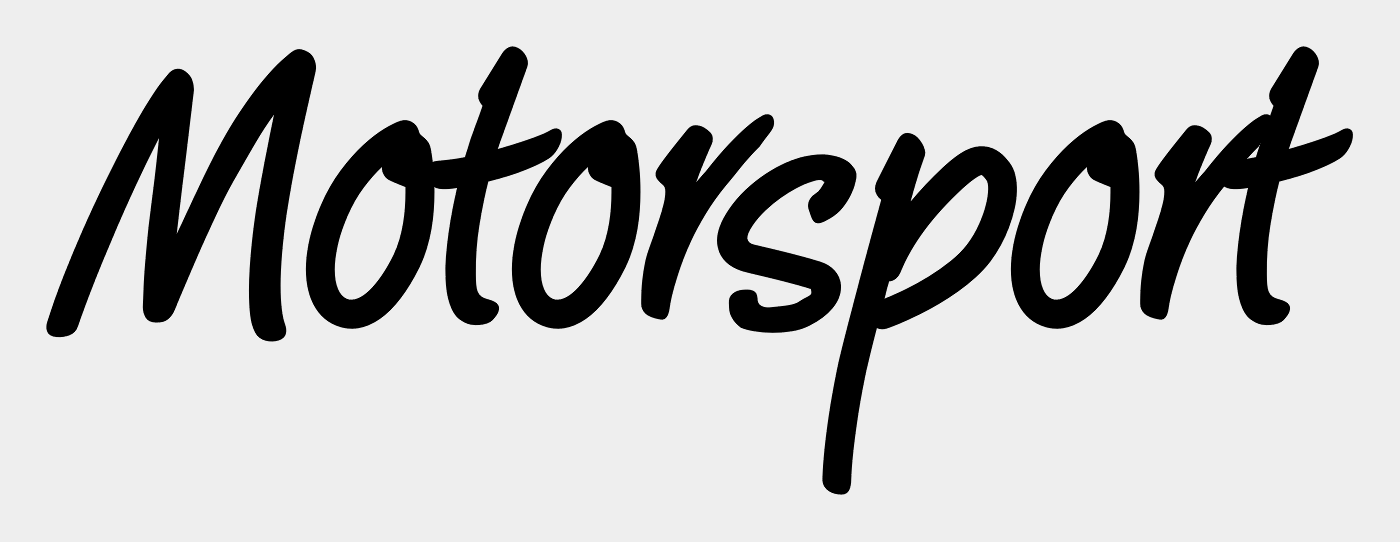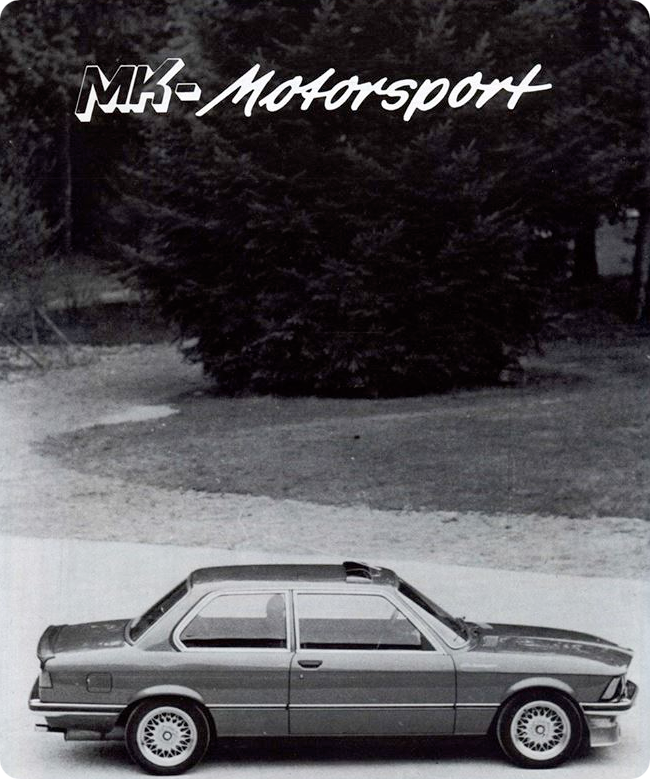
Motorsport-Schriftzug
Könnt ihr mir sagen, um welche Schriftart es sich bei dem "Motorsport" Schriftzug auf dem Bild handelt? Dieser Schriftzug wurde in den 70er-90er Jahren häufig von Tourenwagen- und sonstigen Rennteams  verwendet, weswegen wir das Logo unseres privaten Rallyeteam ebenfalls damit versehen wollen.
Vielleicht wär auch die Peekaboo was …
Von Hand nach rechts neigen und die Anschlüsse anlegen …